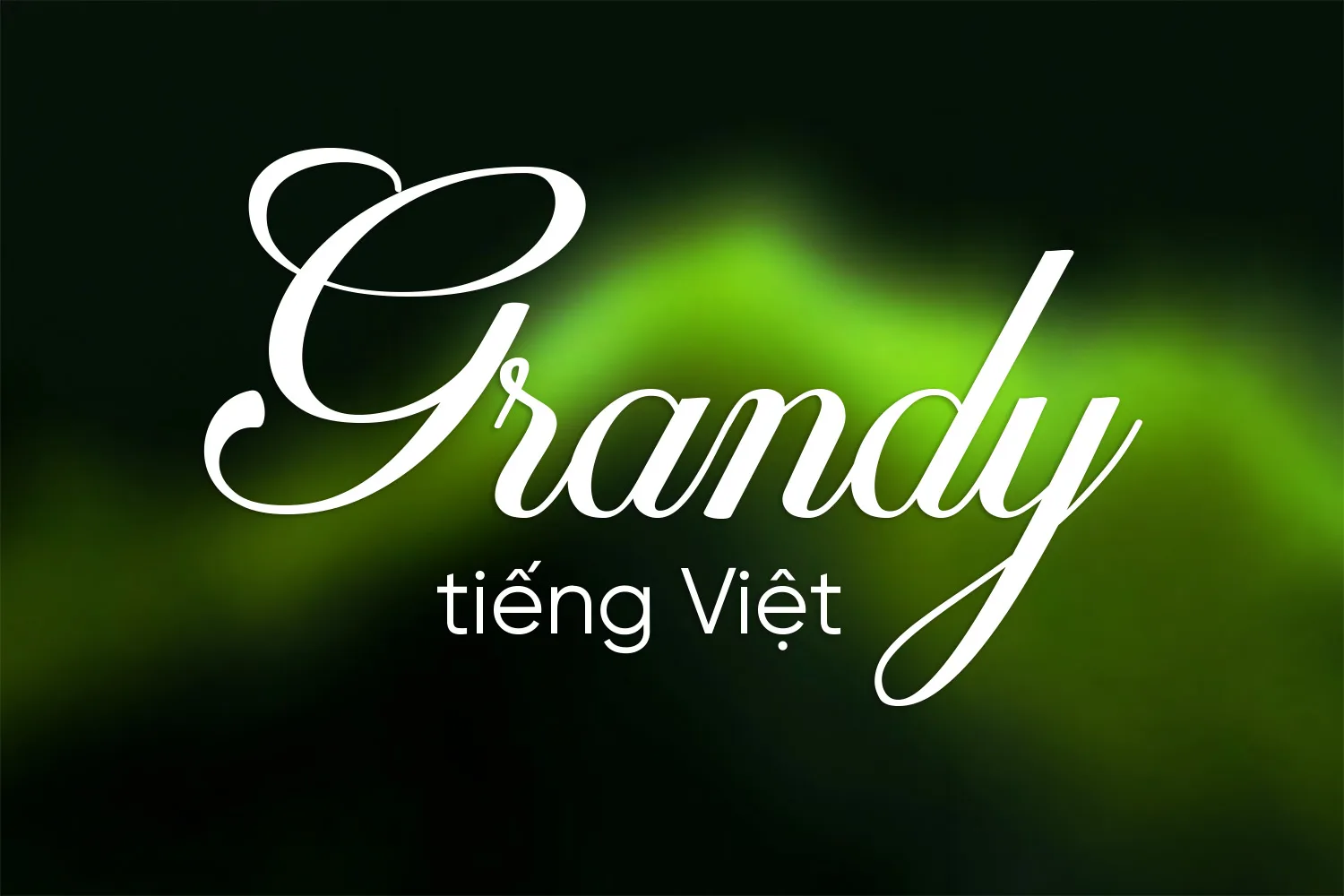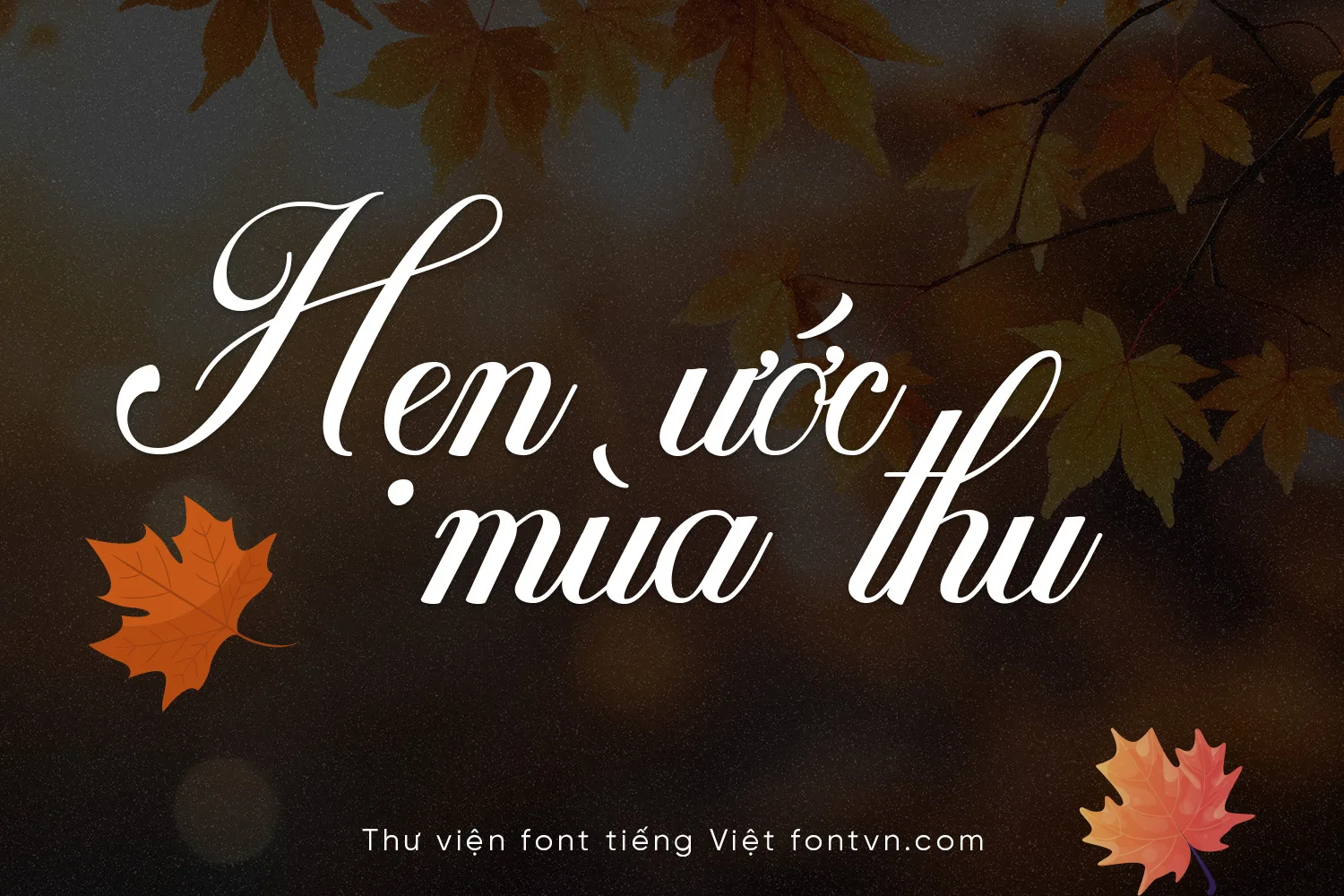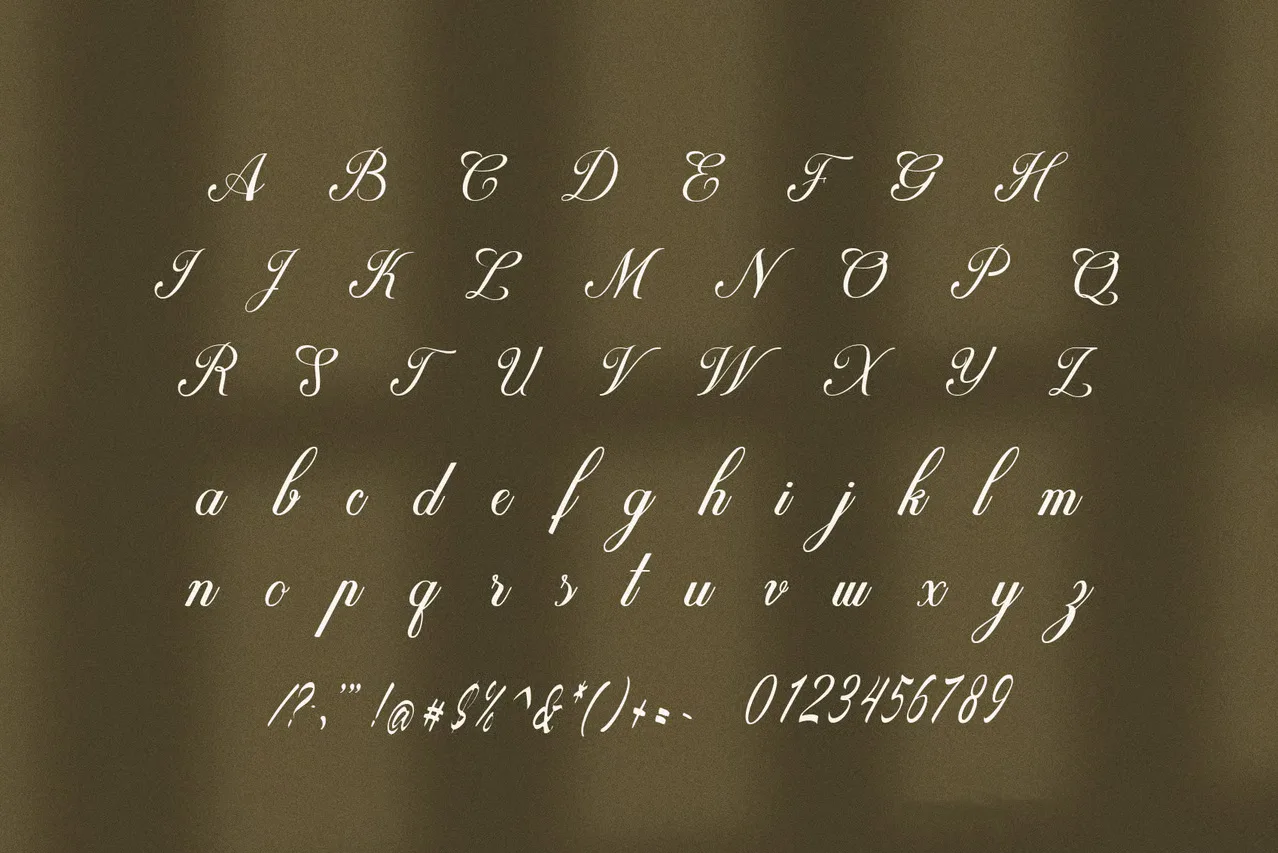
DVN Grandy tiêng Việt – Font Script Calligraphy Sang Trọng & Cổ Điển
DVN Grandy sở hữu phong cách Calligraphy cổ điển với những đường nét thanh mảnh và độ tương phản nét thanh – đậm cực kỳ tinh tế, mô phỏng hoàn hảo kỹ thuật viết tay bằng bút lông ngỗng thời kỳ phục hưng. Điểm nhấn đặc trưng nằm ở hệ thống ký tự in hoa được thiết kế với những đường xoắn (swashes) cầu kỳ, bay bổng, tạo nên một cấu trúc chữ vừa vững chãi vừa uyển chuyển. Tổng thể bộ font mang lại cảm giác sang trọng, quý tộc và đầy tính nghệ thuật, giúp mọi dòng văn bản trở nên sống động và mang đậm chiều sâu thẩm mỹ truyền thống.
Nhờ vẻ đẹp vượt thời gian, DVN Grandy là sự lựa chọn tối ưu cho các dự án thiết kế đòi hỏi sự tinh tế tuyệt đối như thiệp mời sự kiện cao cấp, nhận diện thương hiệu thời trang hoặc bao bì mỹ phẩm sang trọng. Font chữ này phát huy tối đa sức mạnh thị giác khi được sử dụng làm tiêu đề cho bìa sách nghệ thuật, thiết kế logo hoặc các ấn phẩm vinh danh cần sự trang trọng và lịch lãm. Việc kết hợp giữa sự uyển chuyển của nét chữ và các bố cục hiện đại sẽ giúp các nhà thiết kế dễ dàng tạo nên những tác phẩm ấn tượng, nâng tầm đẳng cấp cho mọi sản phẩm sáng tạo.